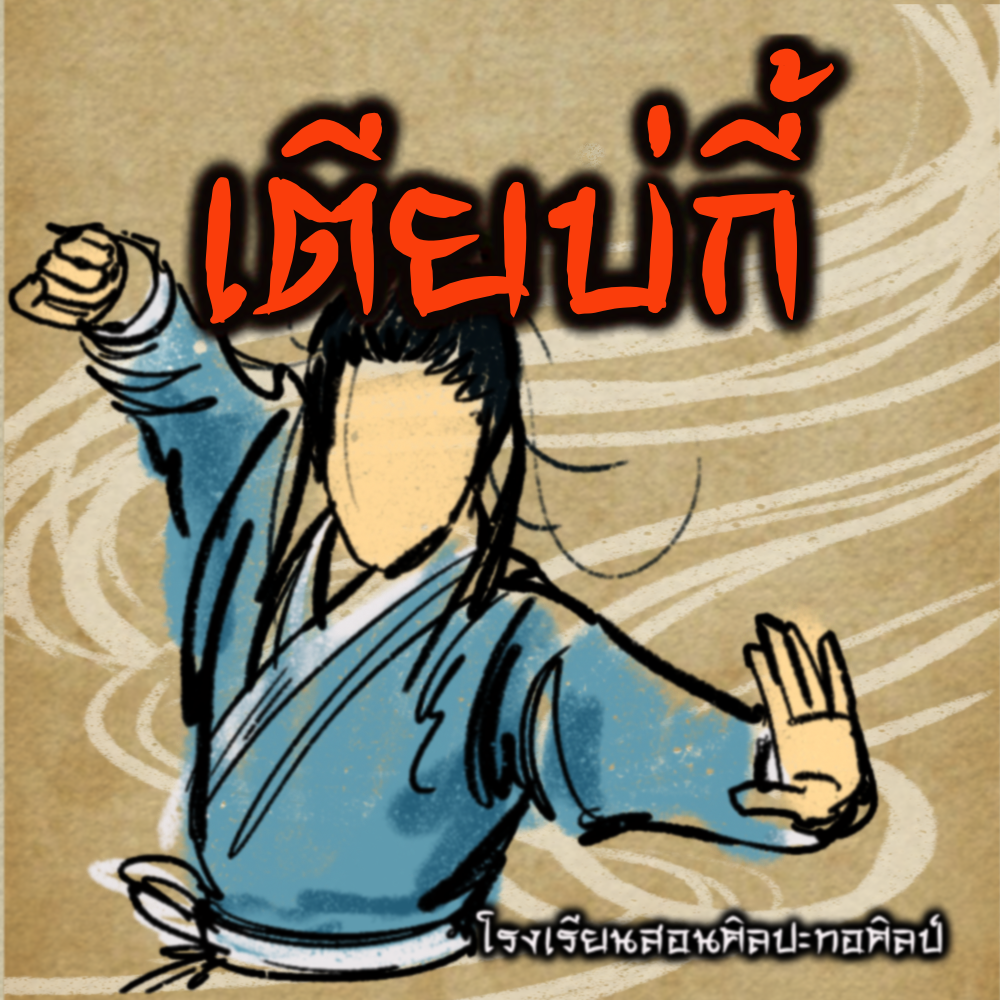
ทอศิลป์-เตียบ่กี้
ชื่อฟอนต์  ทอศิลป์-เตียบ่กี้
ชอบดูซีรี่ส์จีนกำลังภายใน ชอบบุคลิกของเตียบ่กี้
จอมยุทธผู้ผดุงความยุติธรรม มากน้ำใจ
เป็นที่รักของผู้ชิดใกล้ และมีความรักให้ทุกคน
ฟอนต์สไตล์จีนในเมืองไทยมีอยู่แล้วมากแบบ
แต่ก็ยังอยากทำสไตล์นี้ให้มีเพิ่มขึ้นอยู่ดี